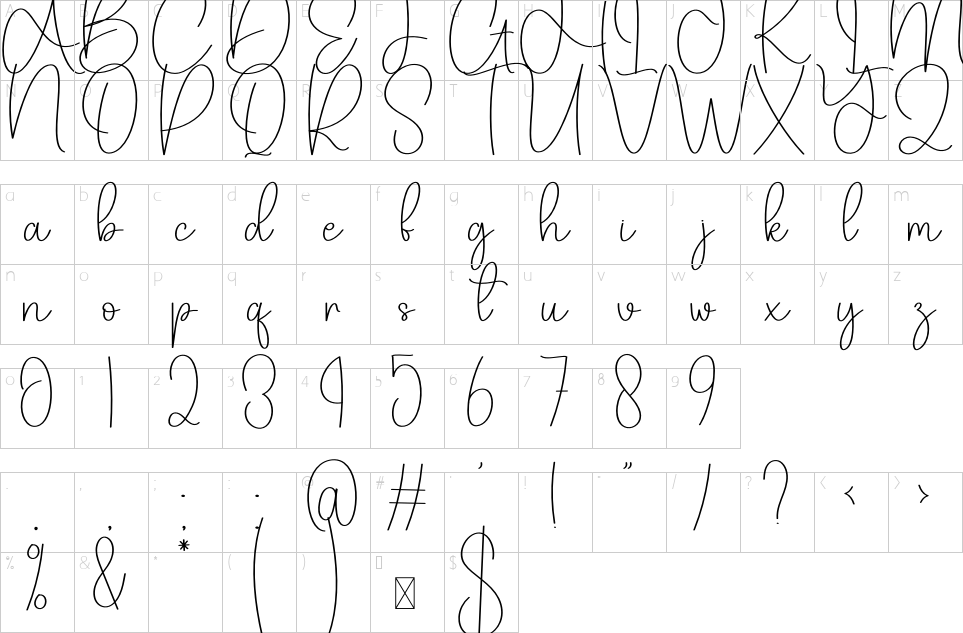
A Maddison Font é uma fonte de graça desenvolvida por scratchones, ideal para aqueles que buscam estilos limpos e modernos em seus projetos de design. Esta fonte é perfeitamente adaptada tanto para uso em seu computador Windows quanto em sistemas Mac. Com 148 downloads, é evidente que a Maddison é uma fonte apreciada entre designers e criadores de arte digital. Ela traz consigo um ar elegante e versátil, capaz de complementar vários estilos de design, seja ele em websites, banners ou até mesmo em trabalhos profissionais. Engajue-se e descubra por si mesmo como a Maddison pode melhorar seu projeto.